在这个网络发展迅速的时代中,字体设计者也成为了时尚的职业。字体设计虽然看似简单,但是对于字体设计者的要求却是很高的。字体设计者不仅要了解经典字体,而且还要有敏锐的艺术性。因为现在字体设计非常的火爆,字体设计者如果想让自己设计的字体得到认可的话,那么就要让自己设计的字体展现出强烈的艺术性和现代感。不过,有些设计师也用其他方法得到了网友们的喜爱,例如设计字体图片,这的确是一种更容易被大众接受的方法。下面,小编将为大家介绍设计字体图片的相关内容。
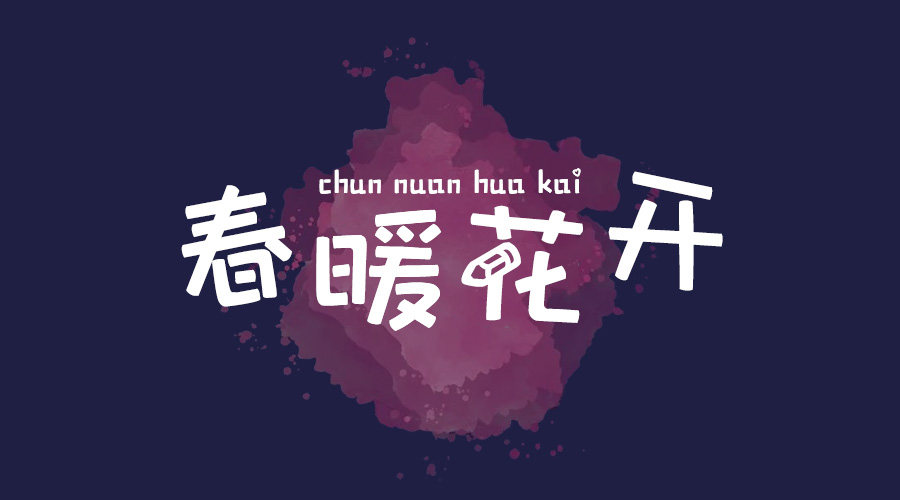
设计字体的方法有很多种,像是叠加法、共用法、俏皮设计法都可以设计出很多有创意的字体。不过这几种方法虽然常用,但是设计出的字体也是如出一辙,很难吸引网友的目光,就让很多字体设计师非常苦恼。其实在发布新字体之前,字体设计师可以先在网络上发布自己做的设计字体图片,似乎更容易让网友对其产生新鲜感。
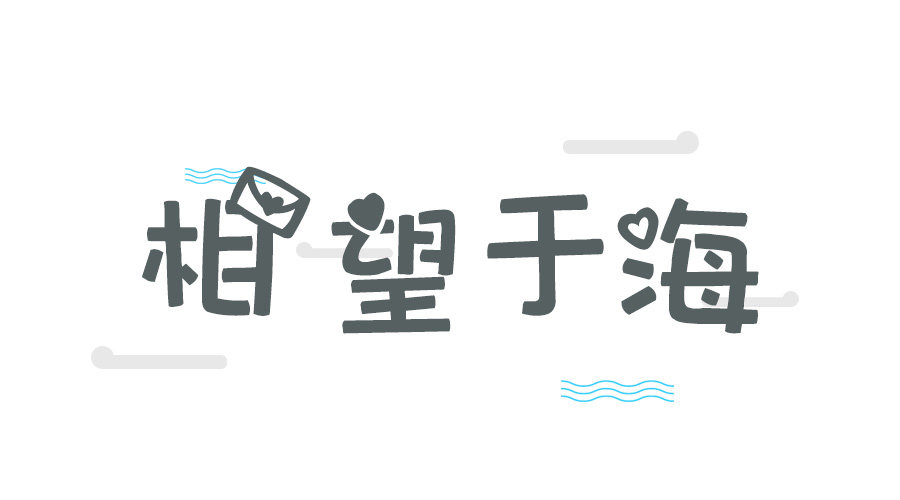
设计字体并不仅是把字体换一种方式展现,而是要字体呈现出一种艺术性与现代感。因为我们平时看到的文字都太过古板,而现代人的审美观却又太超前,所以这就需要字体设计师拥有敏锐的艺术感观。也就是说,设计字体就像是画画一样,所以字体设计师在设计字体之前可以先做出设计字体图片,这样更容易找到灵感,做出设计字体图片也是很多字体设计大师的创意字体的来源。
以上就是小编为大家介绍的关于设计字体图片的相关内容,其实字体设计师可以通过设计字体图片来获取更多的灵感,希望各位字体爱好者可以尝试一下这种方法。